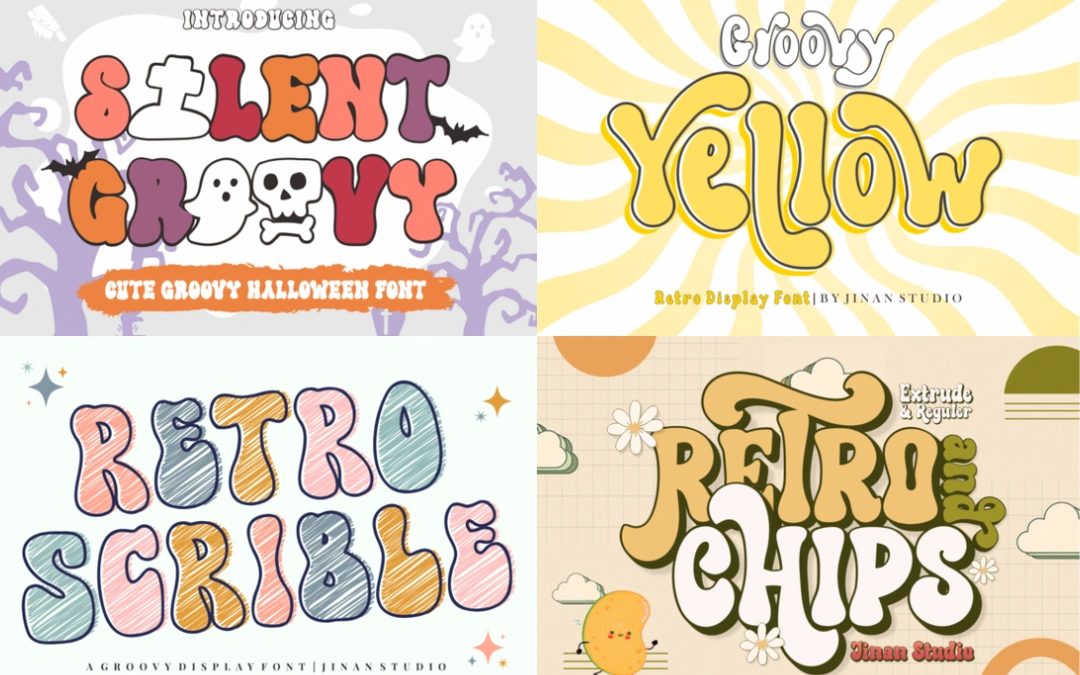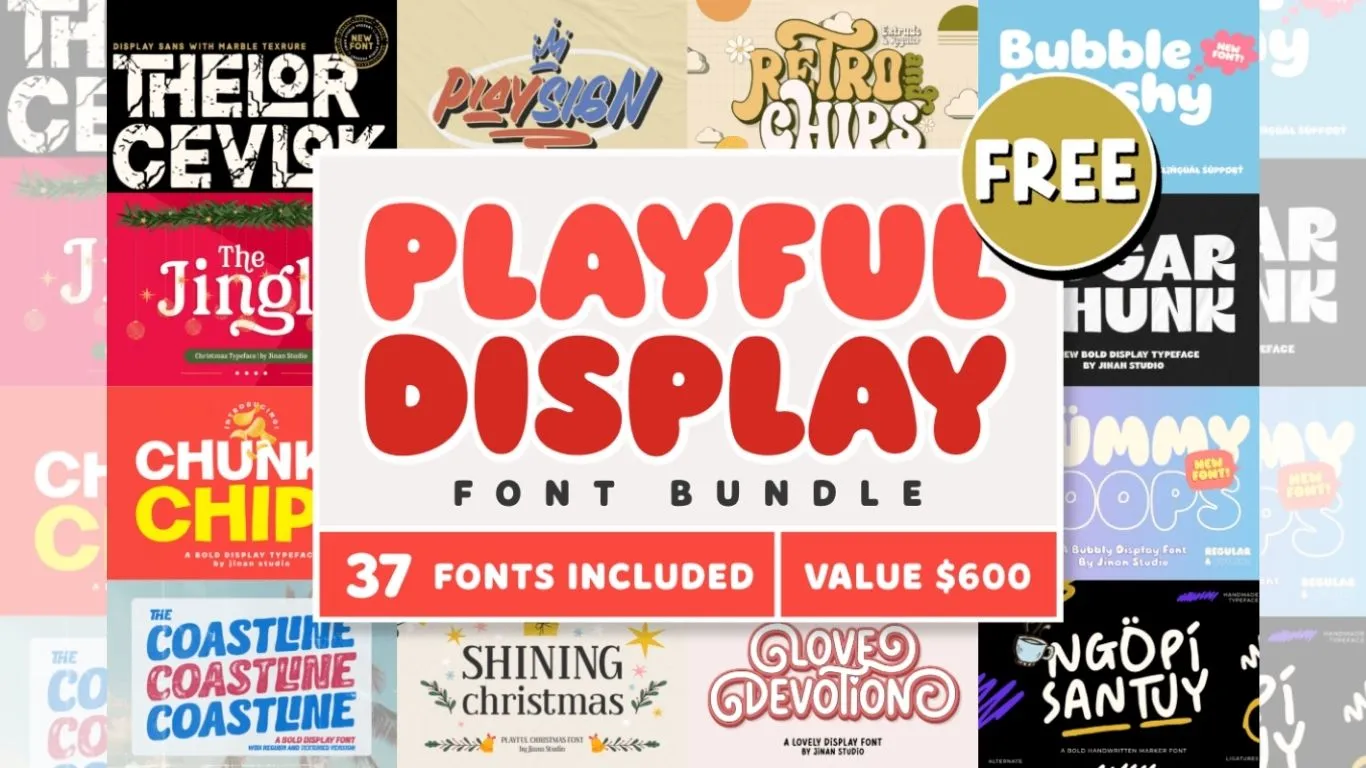
免費英文字體包下載 Playful Display Font Bundle
Creative Fabrica 目前正在限時免費提供 Playful Display Font Bundle,總共包含 37 款字體,從節日氛圍的聖誕字型、帶點黑暗感的 Shadow Cursed,到可愛活潑的 Bubble Hugshy。這套字體包原本需要付費購買,現在只要在限時內免費領取,就能同時獲得個人及商業用途授權,非常划算。
字體包裡有什麼?
共收錄 37 款字體,全部來自設計師 jinanstd,風格多元、各有特色。以下按風格分類整理:
復古 / Groovy 風格
Silent Groovy
Groovy Yellow
Retro Scrible
Retro and Chips
Retro Candy
Groovy Witches
可愛風格
Bubble Hugshy
Gummy Loops
Chunky Chips
Sugar Chunk
Hocus Slime
Milo Glizler Family
節日 / 季節主題
Special Christmas
Christmas Wonderland
Blessed Christmas
Shining Christmas
Easter Monday
The Jingle
Lovely Valentine
手寫 / 展示字體
Franklin Display
Playground
Ngopi Santuy
Love Devotion
Astoria
Corak
Jhino
Clintone
Moreli
Playsign
個性 / 特色風格
-
North Hiking
-
Destitch
-
Shadow Cursed
-
Night Scream
-
Lonely Dripping
-
Helloboo
-
Thelor Cevlok
-
Coastline
-
Playsign